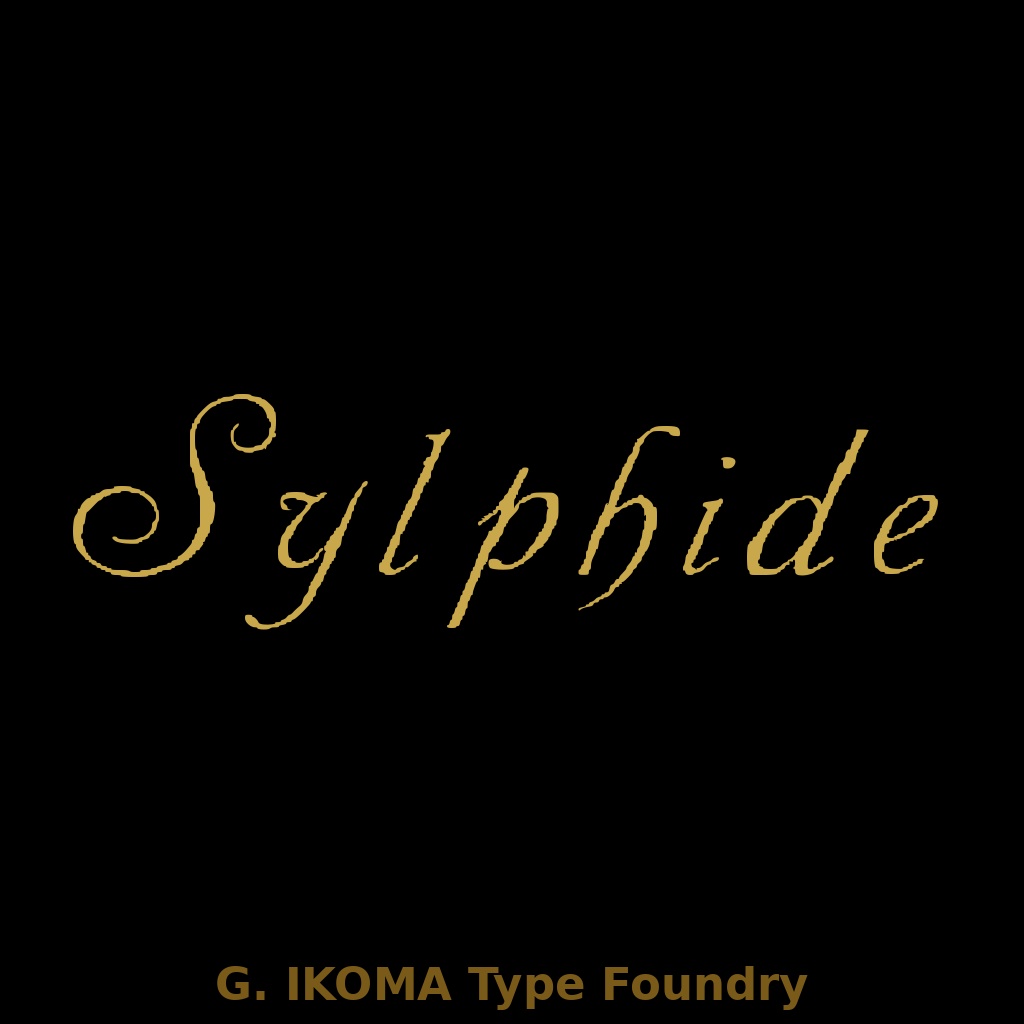
SYLPHIDE — 19世紀欧州印刷資料復元フォント / Historical Revival Typeface [Copperplate Script]
━━━━━━━━━━━━━━━━━━━━━━━━━ 【フォントについて】 ━━━━━━━━━━━━━━━━━━━━━━━━━ **SYLPHIDE** は、19世紀末〜20世紀初頭の欧州印刷資料を原典に、手作業でトレース・デジタル化した復元フォントです。 本作は、ライプツィヒの活字鋳造所 **J. G. Schelter & Giesecke** による銅版彫刻風筆記体をもとに再構成したものです。原典資料には **「ORIGINALERZEUGNIS DES HAUSES J. G. SCHELTER & GIESECKE, LEIPZIG」** と記されています。 細いヘアライン、優雅な傾斜、装飾的なスワッシュを備えた大文字が特徴で、格調ある筆記体表現に適した書体です。 **原典**:Ludwig Petzendorfer, *Schriften-Atlas* または *Schriften-Atlas: Neue Folge* Julius Hoffmann, Stuttgart(パブリックドメイン) **様式**:Copperplate Script / Engraving Script **収録文字**:大文字 A–Z、小文字 a–z、数字 0–9、記号類 **欠落文字**:なし **制作**:株式会社生駒時計店 / G. IKOMA, LTD.(1870年創業) ━━━━━━━━━━━━━━━━━━━━━━━━━ 【ご購入前にご確認ください】 ━━━━━━━━━━━━━━━━━━━━━━━━━ 本フォントは、繊細な細線と装飾的な大文字を特徴とする **ディスプレイ向け筆記体** です。 ロゴ、招待状、ブランド名、装丁などには適していますが、本文組版や小サイズでの長文用途には向きません。 また、原典由来の字形をもとに再構成しているため、現代的な本文用スクリプト書体のような汎用性を前提とした設計ではありません。 ━━━━━━━━━━━━━━━━━━━━━━━━━ 【収録内容】 ━━━━━━━━━━━━━━━━━━━━━━━━━ ・SYLPHIDE.ttf ・LICENSE.txt ━━━━━━━━━━━━━━━━━━━━━━━━━ 【推奨用途】 ━━━━━━━━━━━━━━━━━━━━━━━━━ ・ロゴ ・ブランド名 ・招待状 ・名刺 ・パッケージ ・ウェディング関連デザイン ・装丁 ・ラベル ・バナー画像 ・サムネイル画像 **格調ある筆記体表現を必要とするディスプレイ用途** に適しています。 本文組版や小サイズでの常用には向きません。 ━━━━━━━━━━━━━━━━━━━━━━━━━ 【ライセンス】 ━━━━━━━━━━━━━━━━━━━━━━━━━ 本フォントは、**個人利用・商用利用を問わず**、印刷物、画像、ロゴ、バナー、動画サムネイル等の制作に使用できます。 また、**WebサイトやSNSで画像化された状態で使用することは可能**です。 ただし、以下の行為は禁止します。 ・フォントファイルそのものの再配布、再販売、譲渡、共有 ・改変したフォントファイルの配布 ・本フォントを素材集、テンプレート、デジタル商品等に収録して再販売する行為 ・**本フォントファイルをWebフォントとしてサーバーに設置・配信して利用する行為** ・アプリケーション、ゲーム、ソフトウェア、電子機器等への埋め込み利用 ・AI学習、機械学習、生成モデル訓練等への利用 ・本フォント自体または収録字形そのものについて独占的権利を主張する行為 詳細は同梱の **LICENSE.txt** をご確認ください。 ━━━━━━━━━━━━━━━━━━━━━━━━━ 【原典資料について】 ━━━━━━━━━━━━━━━━━━━━━━━━━ 本フォントは、G. IKOMA, LTD. 所蔵の実物資料をもとに制作しています。 原典資料そのものは本商品に含まれていません。 資料アーカイブについては、下記サイトをご参照ください。 G. IKOMA Archive [https://g-ikoma-archive.netlify.app/](https://g-ikoma-archive.netlify.app/)